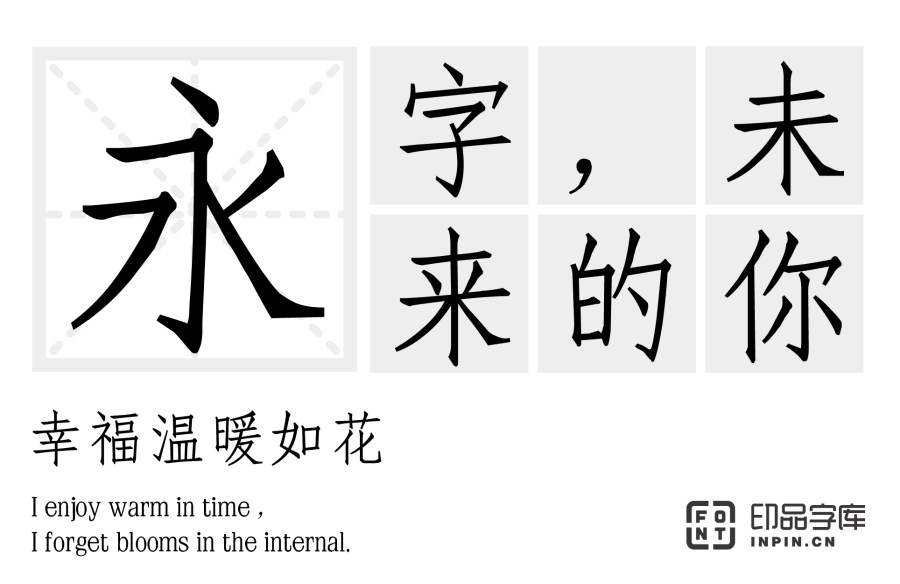
印品仿宋简 细体的创作灵感源于宋体,却又不似宋体般横细竖粗,其各笔画等粗,无太大的差别,起笔和落笔成倾斜形,笔法锐利,结构紧密,笔画秀丽,清秀美观。 印品仿宋简 细体采用宋体结构、楷书笔画,字体较为瘦长平滑,略带棱角,笔画收、尾和转折处常有粗重尖耸的三角形锋角,浑厚凝重,每个单字大多是一个平衡的结构体系,字心聚集,是一种较为规范的雕版字体。 印品仿宋简 细体是一种较为清秀的字体,笔画横竖粗细均匀,书写方便快捷,是印刷字体的一种,适用于排印副标题、诗词短文、批注、引文等,在一些读物中也用来排印正文部分。